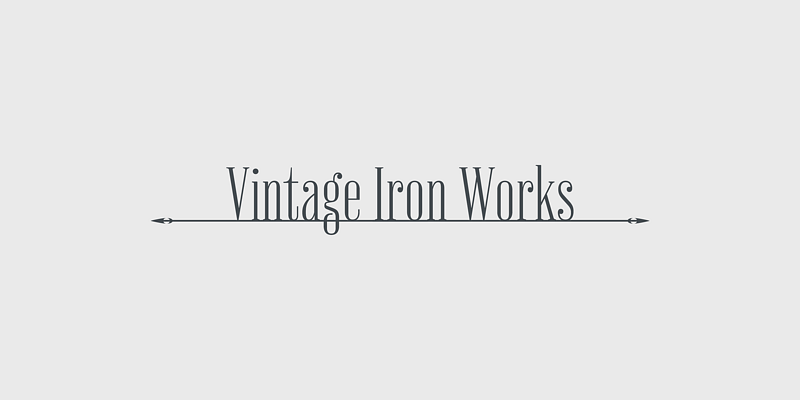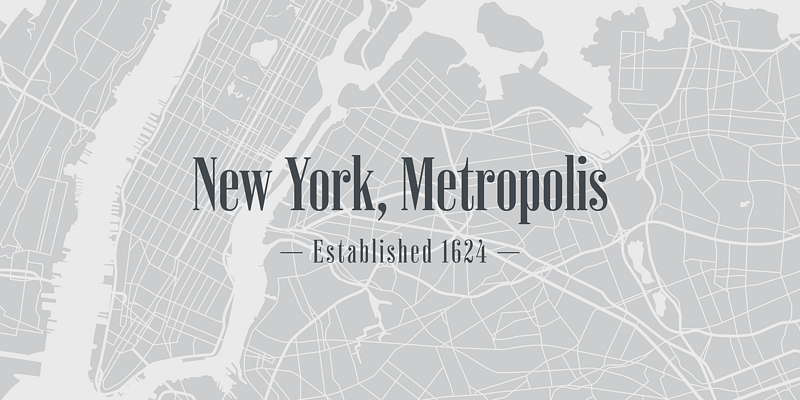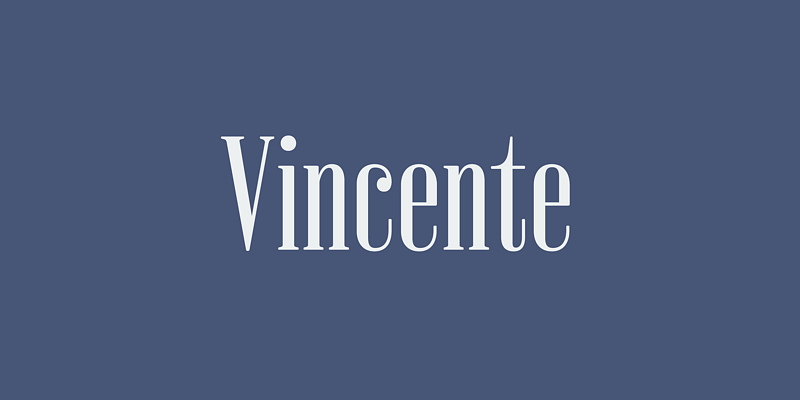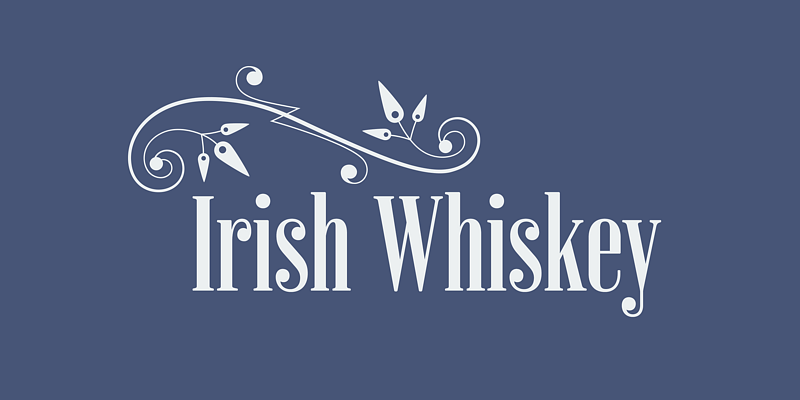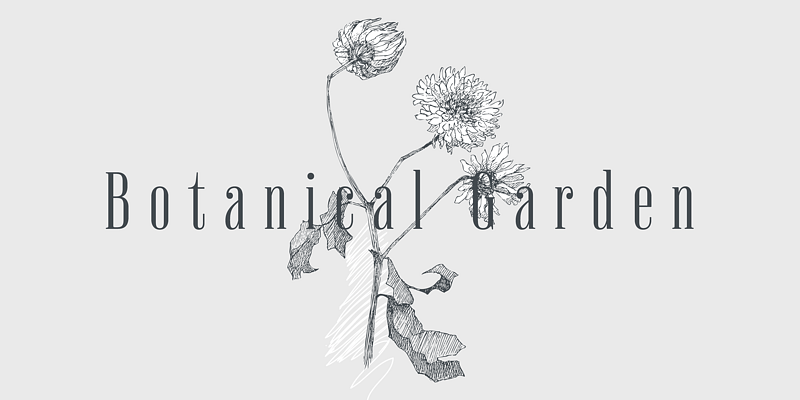
Vincente es una serifa con aspecto de Didone.
Esta fuente no solo tiene curvas industriales sofisticadas, sino también una calidez humana como si estuviese hecha a mano con un deje encantador.